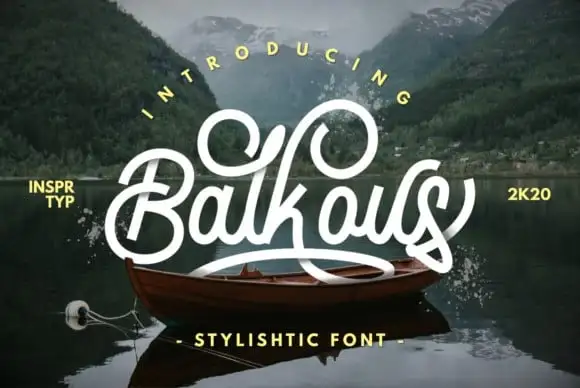
Balkous Script Font – Fonte Grátis
Balkous Script Font
Introduzimos Balkous Script Font – uma nova tipografia Monoline criada à mão que traz letras maiúsculas e minúsculas, números, pontuações e inúmeras variações em cada caractere. Inclui alternativas de OpenType, ligaturas comuns e até mesmo swashes adicionais para personalizar seus projetos. Balkous é um fonte script estiloso e incrivelmente elegante. Suavemente se adapta a uma variedade de necessidades gráficas, como cartões de convite de casamento, cartas de gratidão, citações, cartazes de boas-vindas, logotipos, cards de negócios e quase qualquer outro design que seja capaz de ganhar um toque a mão.